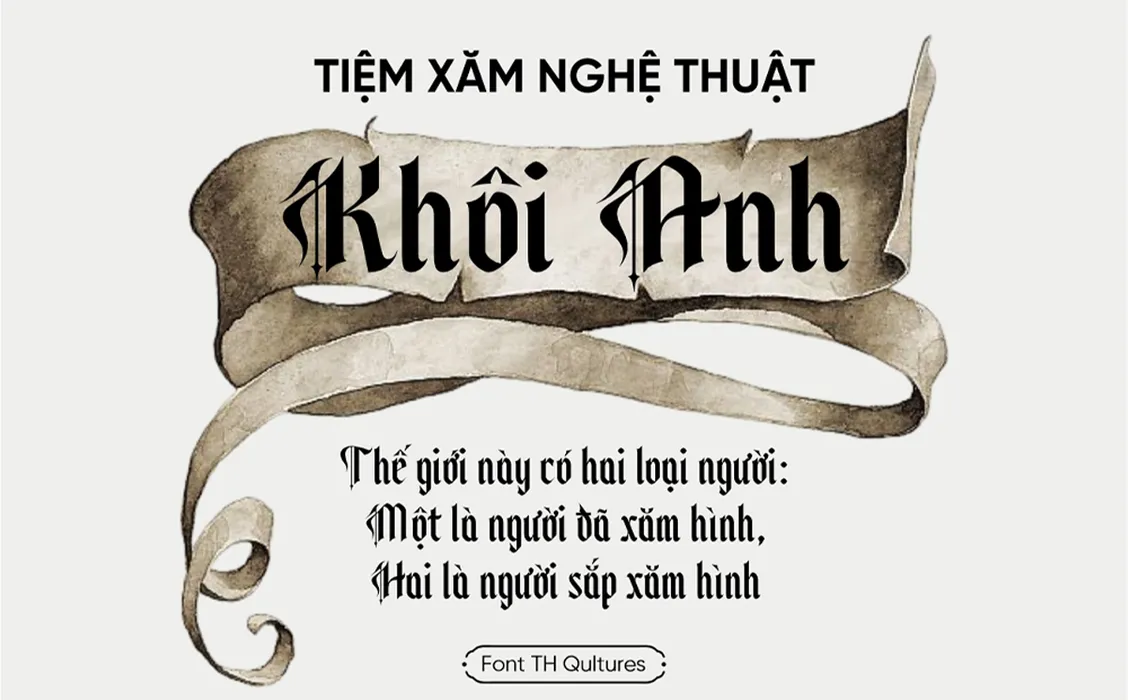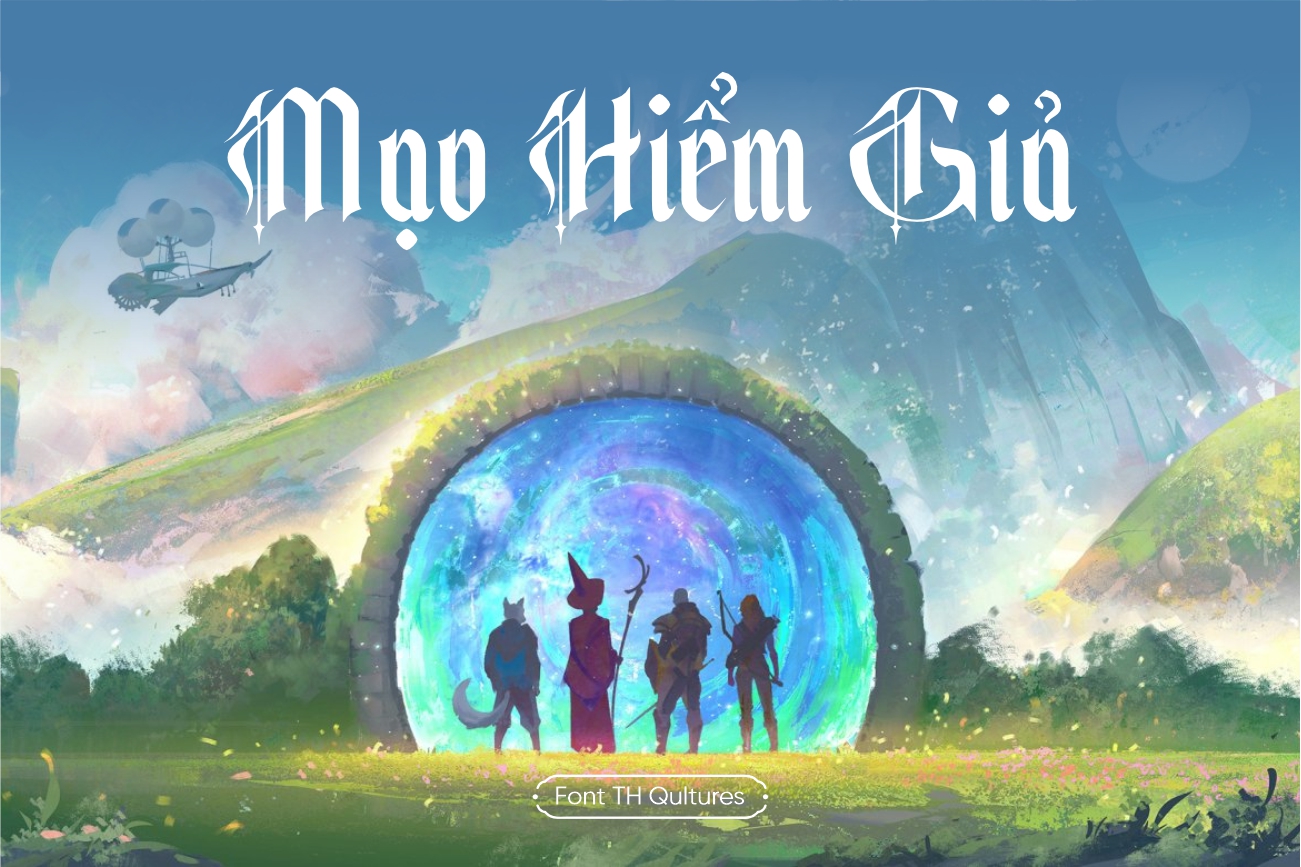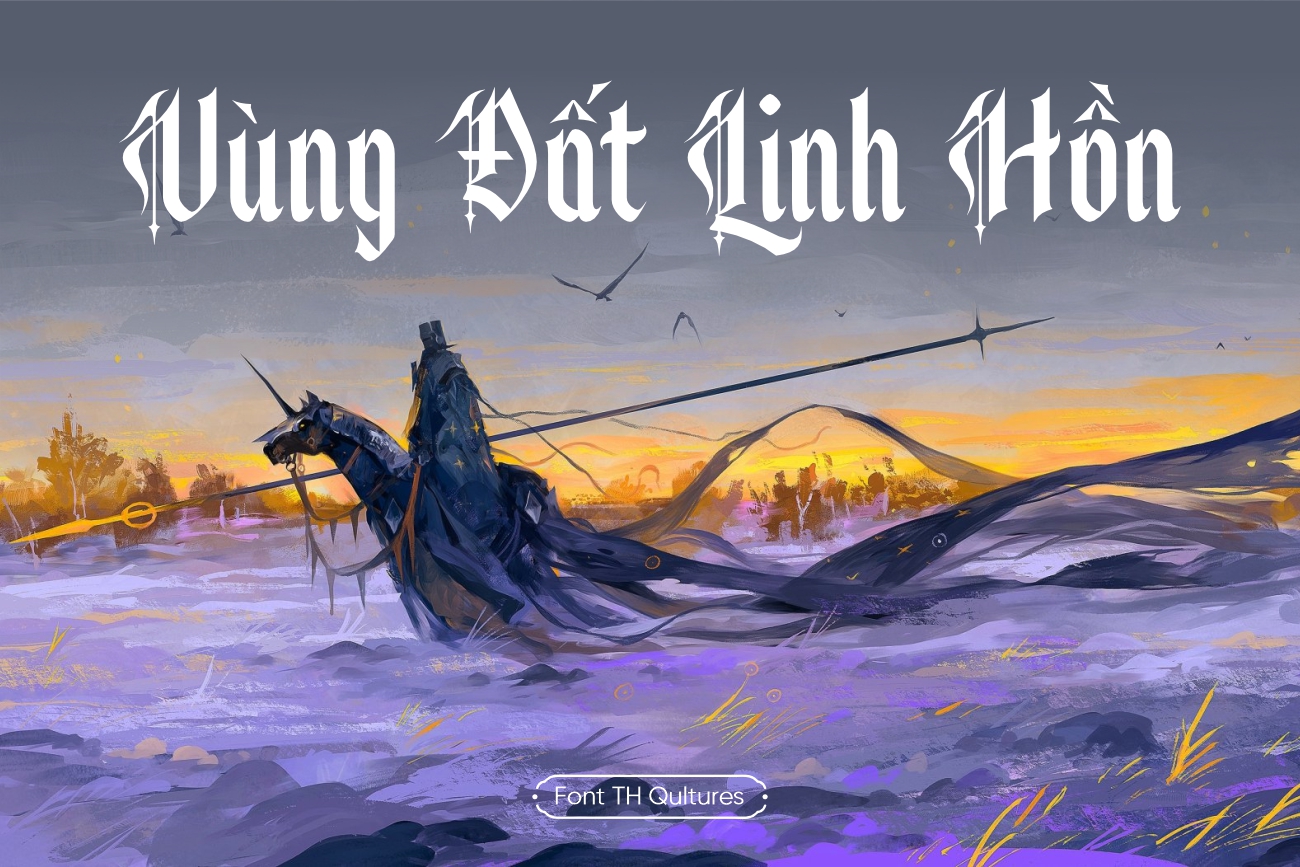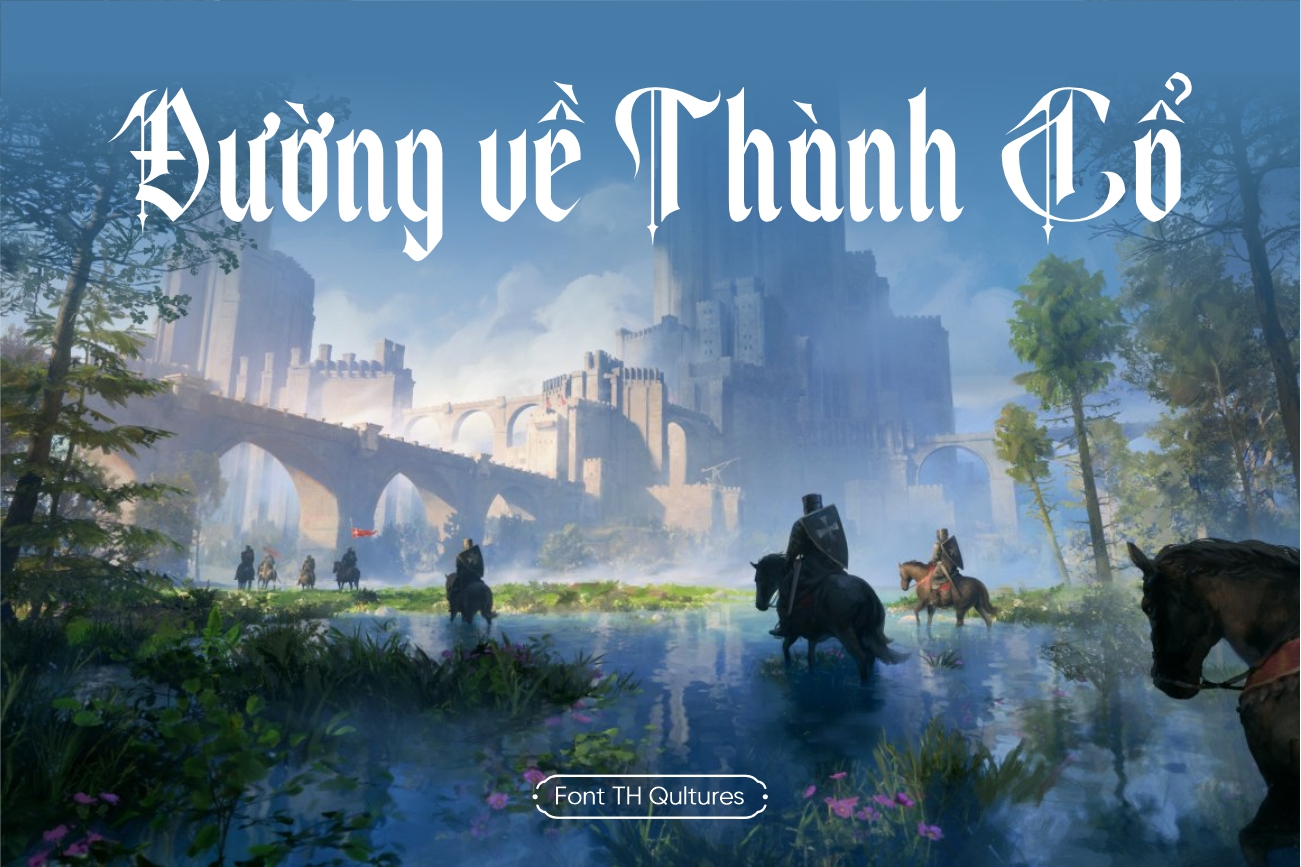
Nếu bạn đang tìm kiếm sự phá cách đầy mạnh mẽ cho các thiết kế mang hơi hướng huyền bí, TH Qultures chính là câu trả lời. Được Việt hóa trọn bộ từ tác phẩm gốc của tác giả Rinto Dwi Nugroho (Almeera Studio), bộ font Gothic (Blackletter) này sở hữu những đường nét sắc sảo, dứt khoát và đầy uy quyền, mang đậm linh hồn thần thoại phương Tây trung cổ được cách điệu hiện đại.
Font chữ tiêu đề game xuất sắc: Phù hợp hoàn hảo cho các dòng game nhập vai (RPG), chiến thuật hay phiêu lưu bối cảnh sử thi, tạo cảm giác hào hùng, gai góc ngay từ cái nhìn đầu tiên.
Ứng dụng đa dạng, đậm cá tính: Sự kết hợp giữa nét xước và chân chữ gãy gọn biến TH Qultures thành lựa chọn sáng giá cho logo rock band, bìa sách kinh dị, poster phim hay biển hiệu tiệm xăm nghệ thuật (Tattoo).
Bản Việt hóa hoàn chỉnh bởi Team TH: Từng dấu câu được chăm chút kỹ lưỡng, đảm bảo các ký tự tiếng Việt hiển thị mượt mà, đồng bộ tuyệt đối với phong cách gốc mà không lo lỗi font.
TH Qultures chính là "vũ khí" thiết kế lý tưởng để bạn tự do thả hồn vào các ấn phẩm truyền thông, banner sự kiện đậm chất nghệ thuật và ma mị.